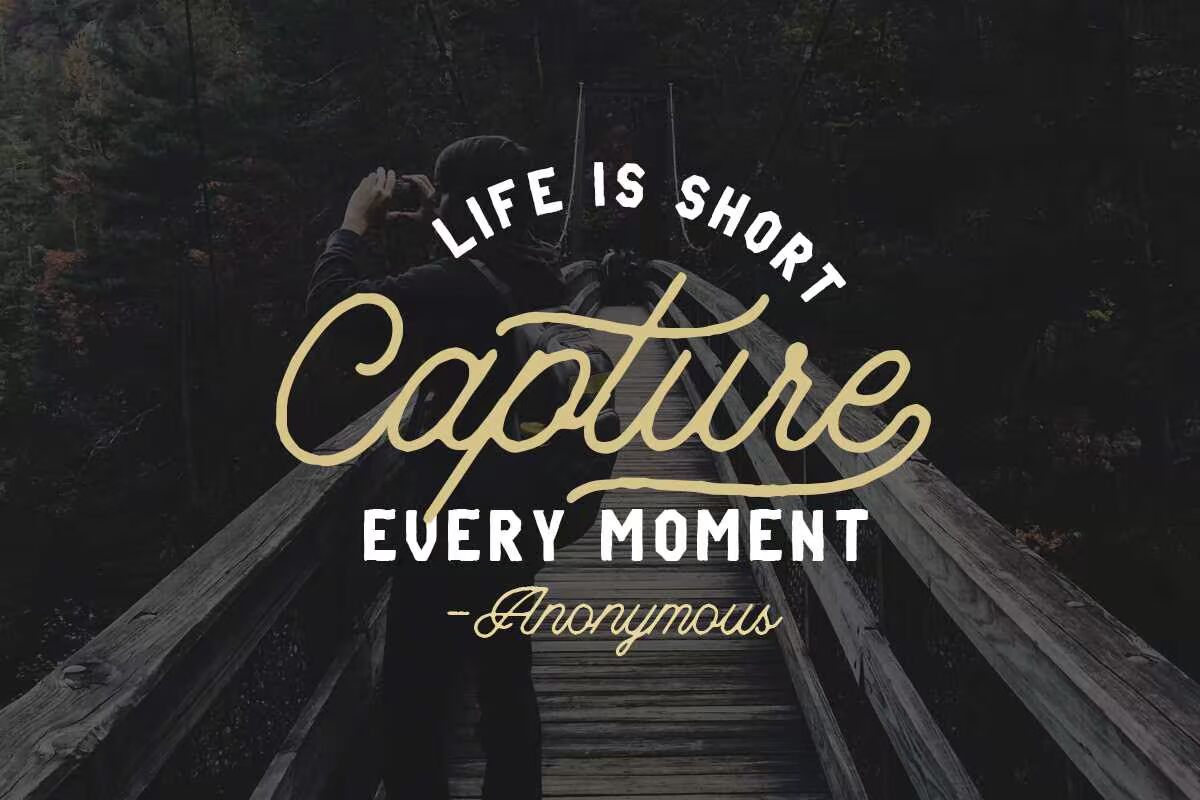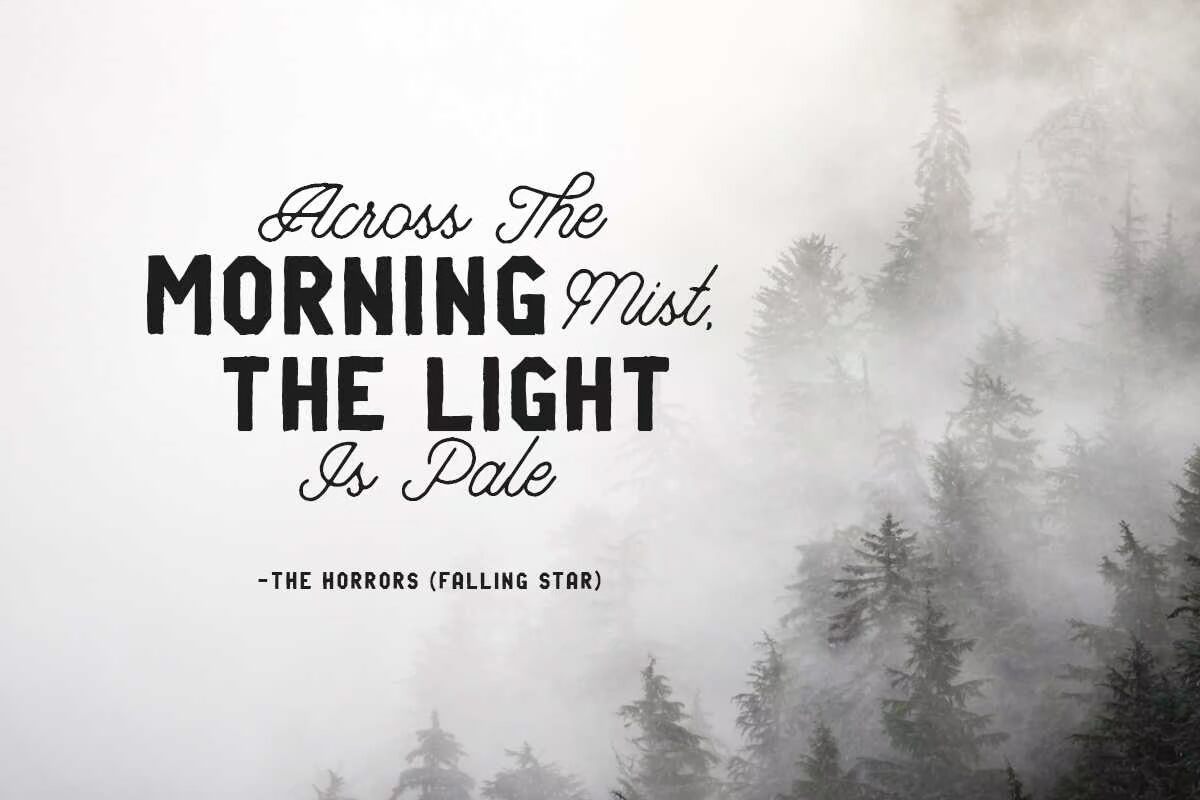
Riverside.A和Mandetypefaces,带有单线和无线。此字体适用于EUSEDASTShirt设计、徽标/品牌、签名、标题、字母引号等。它还包括大写字母、小写字母、标点符号、符号和数字、文体设置替代、连字、,ETCALSO支持多语种。ItalsoalreadyPUAEncoded。Riverside.A和MandeTypeFace带有单行线和sans。此字体适用于EUSEADST设计、徽标/品牌、签名、标题、字母引号等。ItalsoalreadyPUAEncoded包括大写字母、小写字母、标点符号、符号和数字、样式集替换、连字等。ETCALSO支持多语种。ItalsoalreadyPUAEncoded。